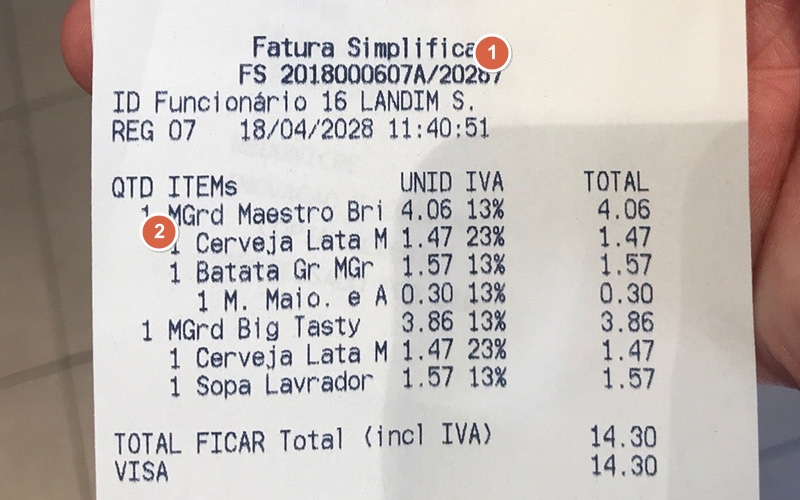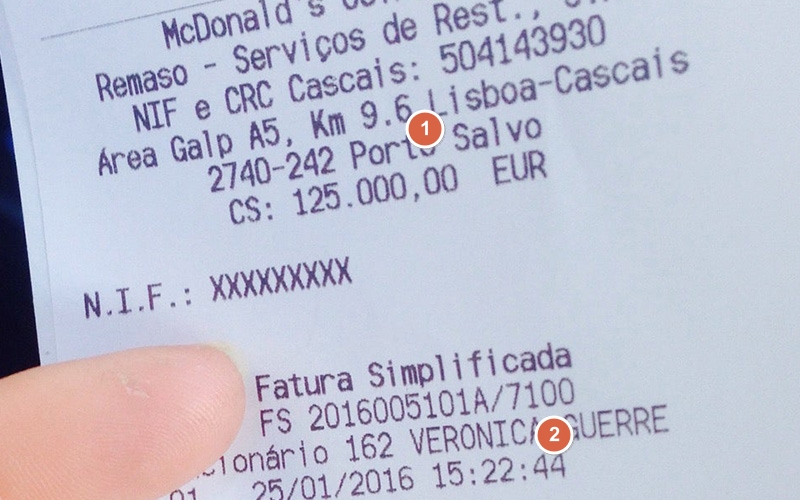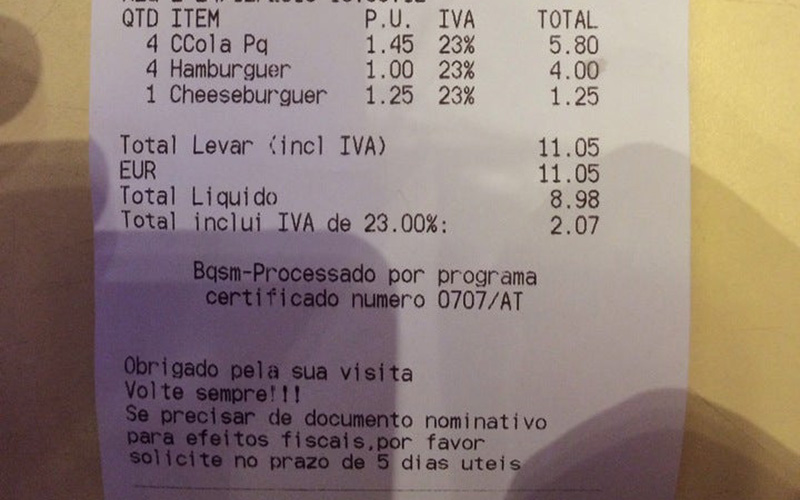
Amostra impressa da fonteM1 para fatura simplificada de McDonald’s em Portugal (❶fonteM1-negrito ❷fonteM1)⤴
Amostra impressa da fonteM1 para fatura simplificada de McDonald’s em Portugal⤴